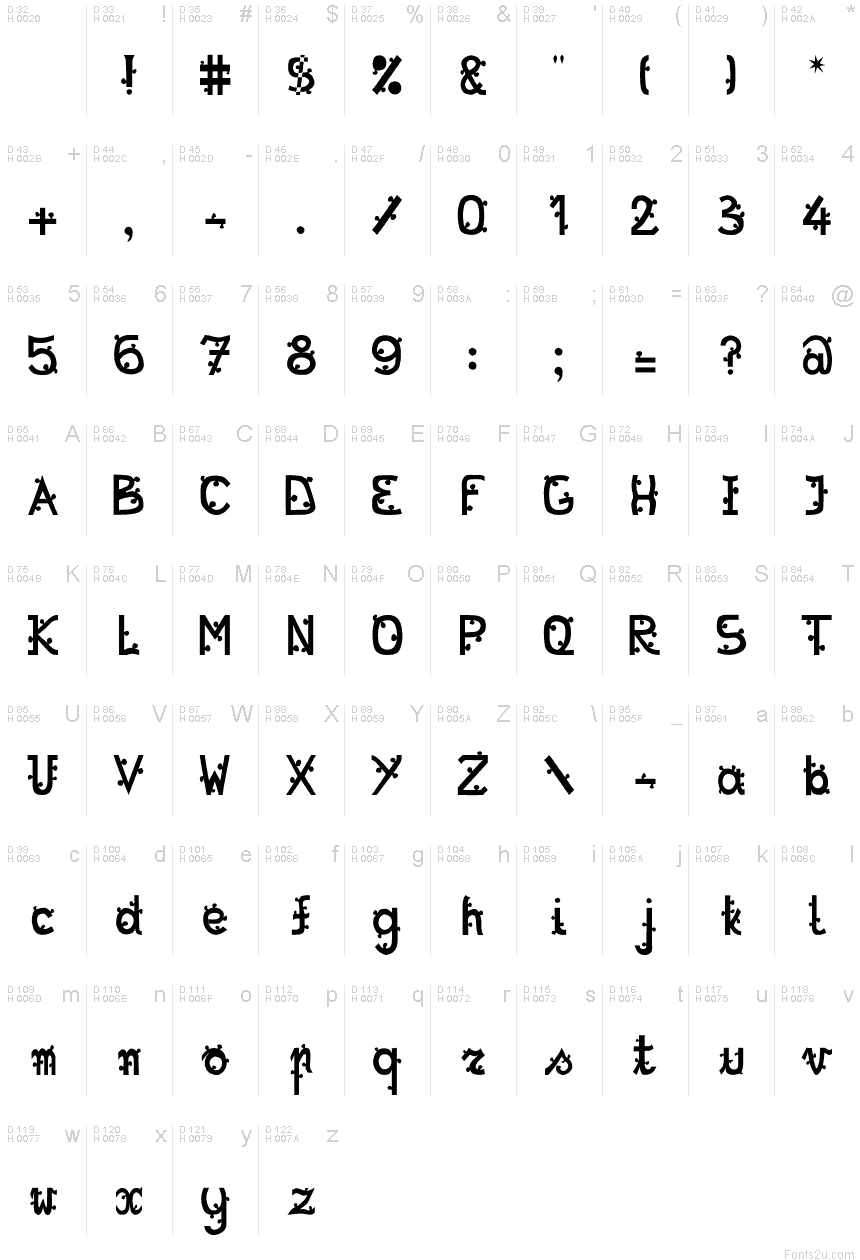
يعد Warts by Mieke 3000 خط عرض مجاني بنمط blackletter بلمسة من روح العصور الوسطى المشاكسة. تجمع الحروف بين الزوايا الحادة التي تشبه الأعلام والنتوءات المنتفخة التي تلتصق بالخطوط، مما يمنح الخط طابعاً يمزج بين اللافتات القوطية المرسومة يدوياً وتلك الخطوط الغريبة التي نجدها في كتب القصص الخيالية.
هذا المزيج مثالي لعناوين الملصقات، ومنشورات الهالوين، وأغلفة كتب الفانتازيا، وشعارات الفرق الموسيقية، وتصاميم الحانات أو المهرجانات حيث تحتاج إلى خط مجاني يضفي طابعاً مميزاً بسرعة. كما أنه يعمل بشكل رائع للعناوين القصيرة وبطاقات العناوين، لأن تلك النتوءات العقدية والأشكال المدببة تمنح حتى بضعة أحرف لمسة حادة تشبه شعارات النبالة.